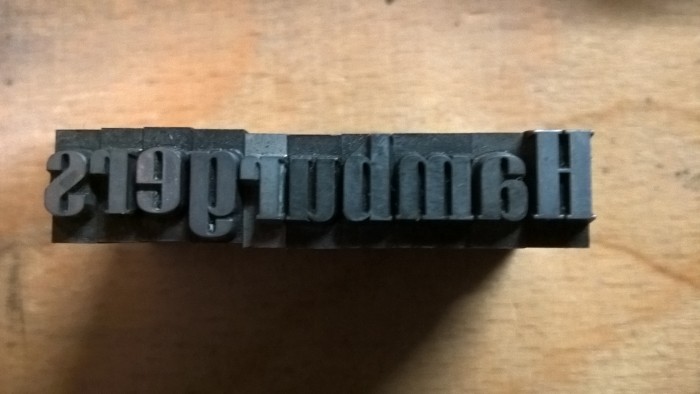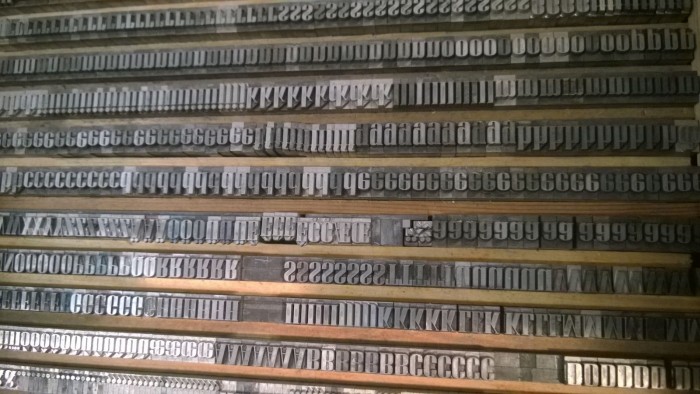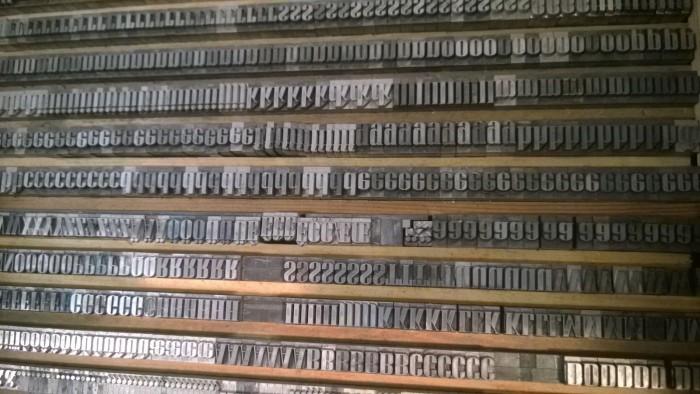
Prägnantes C - welche Schrift?
noch eine Schrift, deren Name ich nicht herausfinden kann. Ich fand das "C" recht prägnant.
Wer kann mir helfen, die Schublade korrekt zu betiteln?
Der Witz bei der Sache: Diese Schrift findet sich in den Seemann-Nachträgen aus der NS-Zeit unter den "Neudeutschen Schriften",also zusammen mit den gerade so heiß diskutierten Schaftstiefelchen.
In diesem Falle wohl eine unverdächtige Form - oder, "Patria" (Vaterland) vielleicht ein Wolf im Schafspelz? Wer war H.-R. Möller? Hatte er Völkisch-Nationalistische Gedanken? War er gar ein Nazi?
Hier wird die "Maximum" von ihm gezeigt:
Aber auch in jenem thread hieß es schon, dass der Herr wohl eher unbekannt ist.